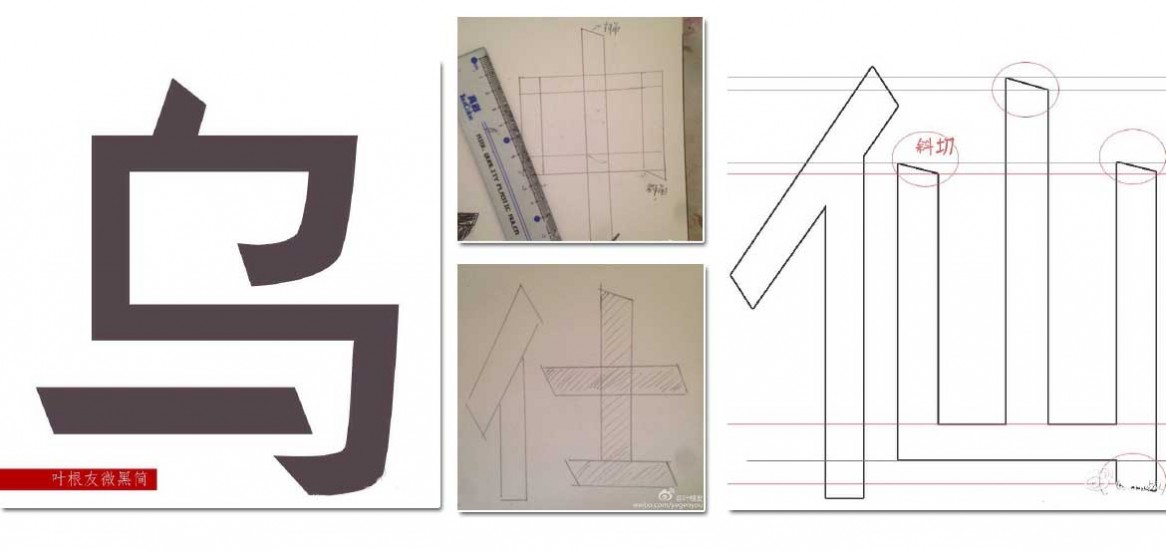
葉根友微黑
字體作者:葉根友
創(chuàng)作年代:2014年
字體字?jǐn)?shù):6763個(gè)中文漢字以及其他英文字母和阿拉伯?dāng)?shù)字
字體介紹
葉根友微黑簡(jiǎn)體是一款正規(guī)的黑體類型的印刷體,整個(gè)字體輕松活潑而有時(shí)代鮮明的特征,整個(gè)筆畫(huà)橫度微斜切,干凈而大氣,簡(jiǎn)約是這款字體的主要特色。每個(gè)筆畫(huà)15度斜角的設(shè)計(jì),使整個(gè)字型看起來(lái)更具時(shí)尚大氣,在應(yīng)用于內(nèi)文、標(biāo)題等都是不錯(cuò)的選擇,葉根友微黑從設(shè)計(jì)到制作歷時(shí)數(shù)年,工程量是普通手寫(xiě)字體的數(shù)倍,每個(gè)筆畫(huà)和結(jié)構(gòu)架次都需要經(jīng)過(guò)精心布局,以求好的效果呈現(xiàn)給用戶。
設(shè)計(jì)初稿